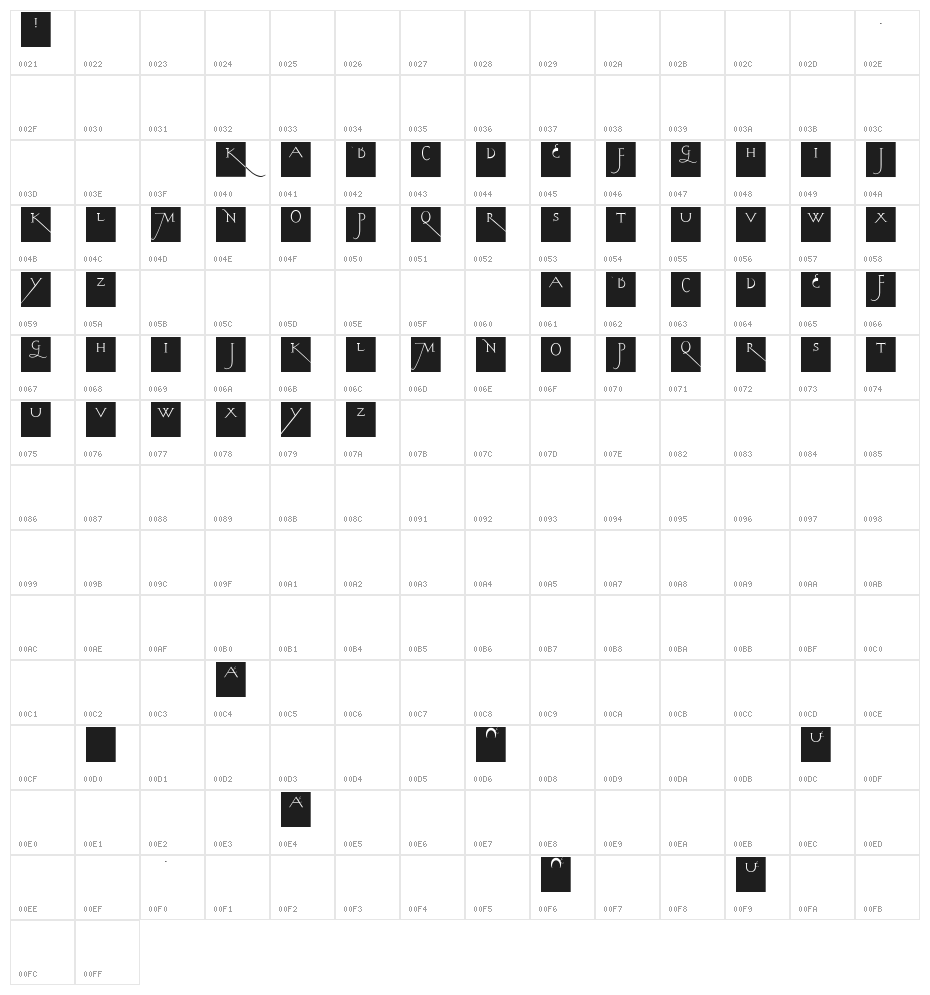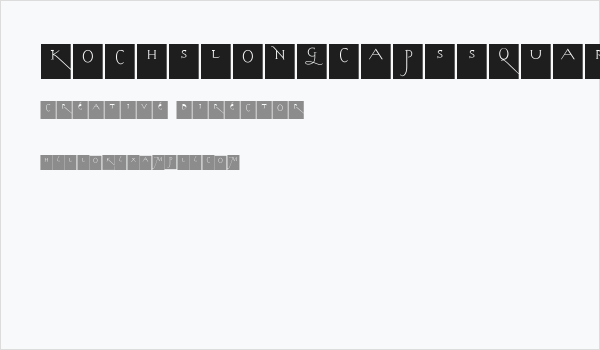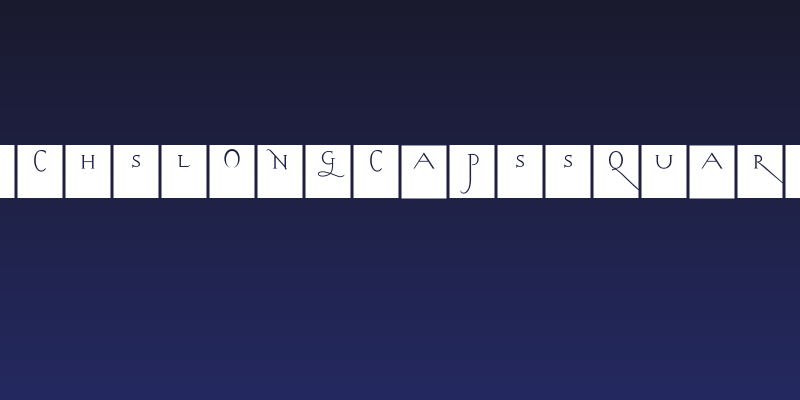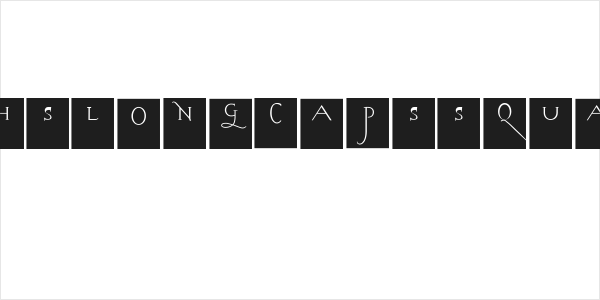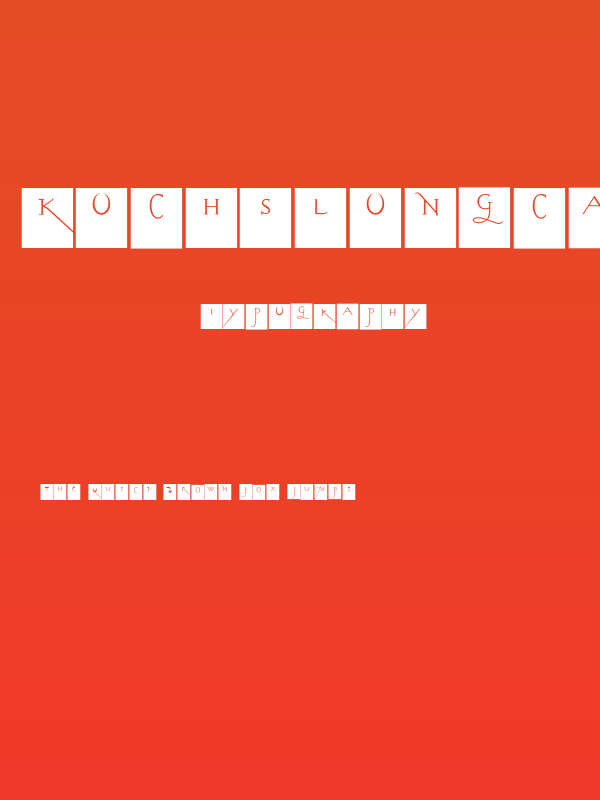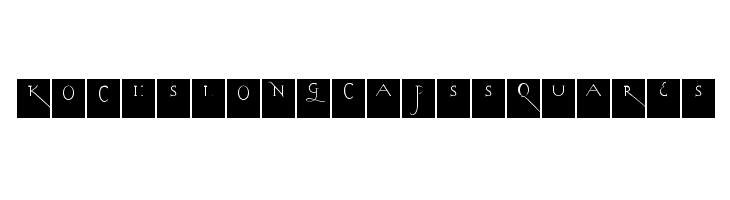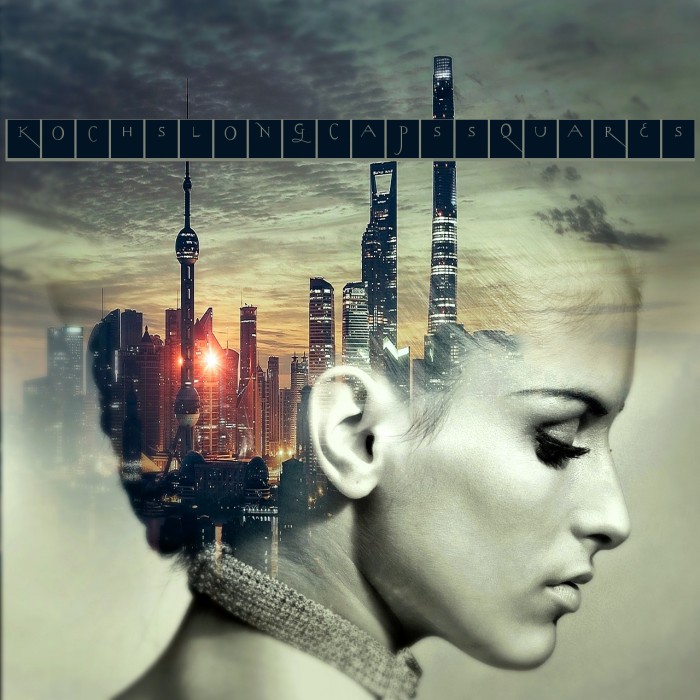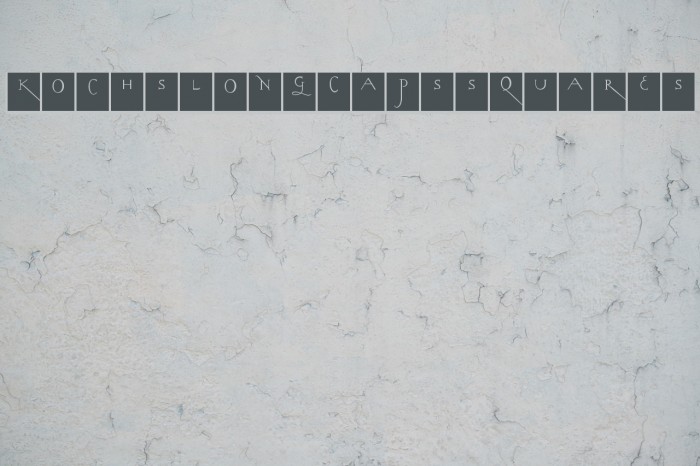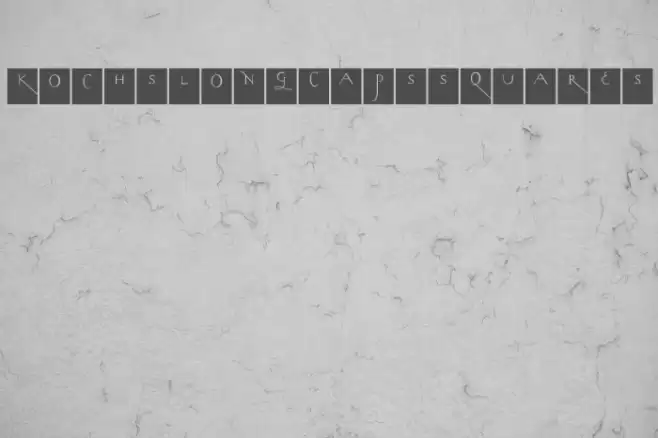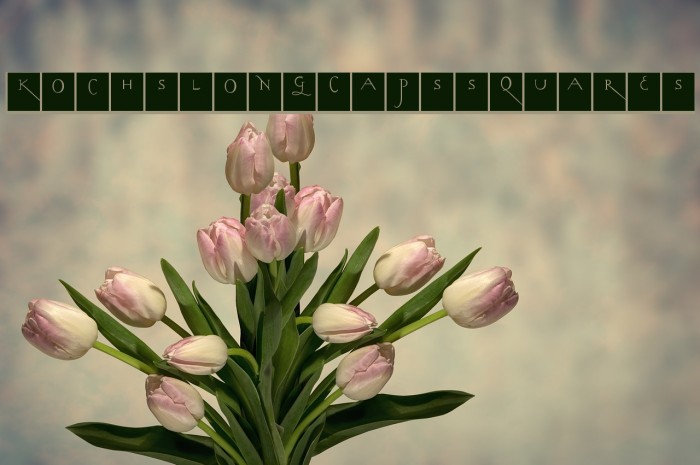
KochsLongCapsSquares Font
| Caso de uso | Logos, Headlines, Invitations |
| Projetos propostos | Ideal for use in branding, logo design, invitations, and decorative headings where a touch of elegance and uniqueness is desired. |